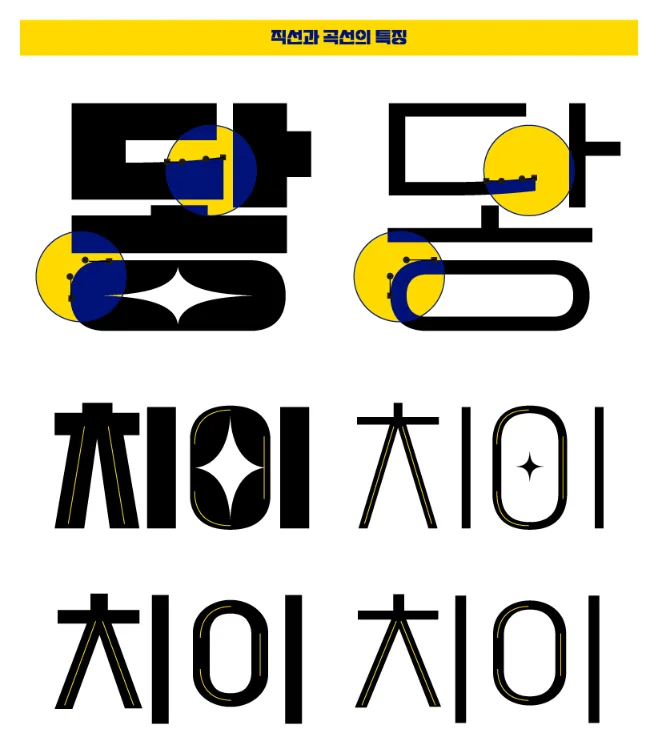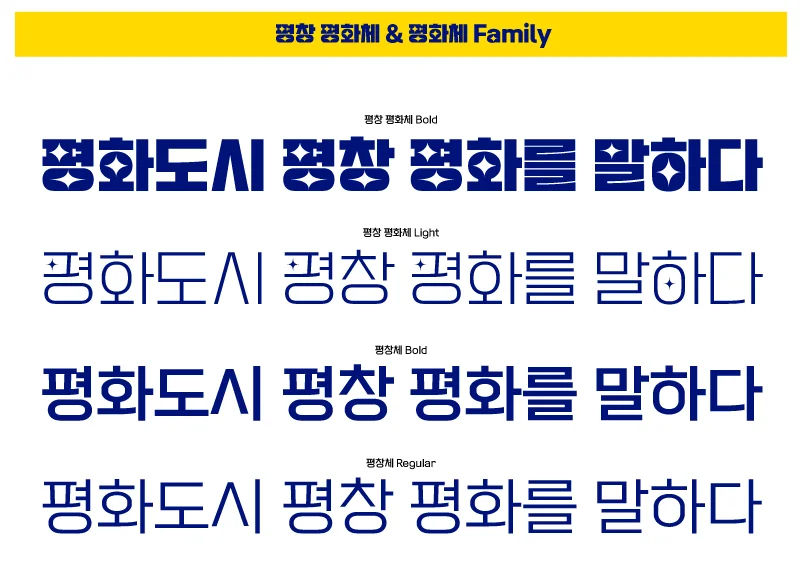
디자인 작업을 하다 보면 늘 같은 고민에 빠집니다. "어울리는 폰트가 없을까?" 특히 제목이나 배너, 썸네일처럼 임팩트가 필요한 작업에서는 개성 있는 서체 하나가 전체 완성도를 좌우하기도 합니다. 오늘 소개할 평창평화체는 공공기관에서 제작했지만, 그 어느 상업 폰트에도 뒤지지 않는 개성과 퀄리티를 자랑하는 서체입니다. 개인·상업용 모두 완전 무료로 사용할 수 있다는 점도 큰 장점입니다.
1. 평창평화체란? — 탄생 배경
평창평화체는 강원특별자치도 평창군이 공식 제작한 전용 서체입니다.
개발의 시작은 2020년 평창군 시책보고회로 거슬러 올라갑니다. 당시 회의에서 서체를 활용한 지역 홍보 및 2018 평창동계올림픽의 유산인 평화의 가치 확산이라는 목적 아래 개발 사업이 발굴되었습니다. 실질적인 작업은 2021년 5월에 착수했고, 약 11개월의 개발 기간을 거쳐 2022년 4월 공식 발표·공개되었습니다.
단순히 지자체가 기획만 한 것이 아닙니다. 개발 실무는 산업통상자원부 산하 준정부기관인 한국디자인진흥원이 맡았고, '윤명조', '윤고딕' 등으로 널리 알려진 ㈜윤디자인그룹이 지정사업자로 참여해 서체의 전문성과 완성도를 높였습니다.
이번 사업으로 총 4종의 서체가 개발되었습니다. 제목용 서체인 평창평화체 2종(Light·Bold)과 본문용 서체인 평창체 2종(Regular·Bold)이 그것입니다. 이 글에서는 그 중 평창평화체를 집중적으로 소개해 드립니다.
2. 디자인 콘셉트 — '평화의 빛'을 담다
평창평화체의 핵심 디자인 키워드는 단 하나, '빛(光)'입니다.
2018 평창동계올림픽의 유산인 '평화'를 상징하는 형태로, 빛을 형상화한 디자인이 특징입니다. 서체에는 빛의 두 가지 속성이 반영되어 있는데, 빛의 강렬함은 굵은 선(Bold)으로, 은은하고 부드러운 빛의 여정은 얇은 선(Light)으로 표현했습니다.
글자 곳곳에 빛이 퍼져나가는 듯한 포인트 형태가 들어가 있어, 일반 고딕체와는 확연히 다른 개성 있는 비주얼을 연출합니다. 배너, 썸네일, 포스터처럼 한눈에 시선을 끌어야 하는 제목용 작업에 특히 잘 어울리는 서체입니다.
| 굵기 | Light, Bold 총 2종 |
6. 활용 팁 및 페어링 서체 추천
평창평화체 추천 활용 분야
- 블로그·SNS 썸네일: 제목용 서체 특유의 강한 존재감으로 시선을 끄는 데 효과적입니다.
- 배너 및 포스터 디자인: 빛 포인트 덕분에 팝아트, 레트로 스타일과 잘 어울립니다.
- 영상 타이틀 자막: Bold는 강렬한 임팩트, Light는 세련된 분위기를 연출합니다.
- 지역 축제·행사 홍보물: 공공 서체 특유의 신뢰감과 개성을 동시에 살릴 수 있습니다.
- 간판·안내판·조형물: 평창군이 도시 시각 디자인에 활용하는 공식 전용 서체입니다.
평창평화체는 제목용 서체이므로 본문용 서체와 함께 쓰는 것이 기본입니다. 같은 패키지로 개발된 평창체(본문용, Regular·Bold 2종)와 세트로 활용하면 통일감 있는 비주얼을 완성할 수 있습니다. 제목부터 본문까지 평창 서체 패밀리만으로 완결된 디자인을 구현하는 것도 충분히 가능합니다.
공공기관에서 만든 서체라 해서 가볍게 여겼다면 오산입니다. 한국디자인진흥원과 윤디자인그룹이라는 전문 기관의 손을 거쳐 완성된 평창평화체는 상업 폰트와 견주어도 손색이 없는 완성도를 자랑합니다. 무료이고, 개성 있고, 합법적입니다. 2018 평창동계올림픽의 평화 정신을 담은 이 서체를 작업물에 적극 활용해 보시기 바랍니다.